Minuskelziffern
Typografischer und paläografischer Terminus für die Indo-Arabische Ziffern 1, 2, 3, 4, 5, 6, 7, 8, 9 und 0 mit variierenden Oberlängen und Unterlängen im Vierliniensystem (Schriftlinien). Primär als Mediävalziffern, auch als Gemeine Ziffern, Charakterziffern oder in seltenen Fällen auch als Nautische Ziffern bezeichnet.
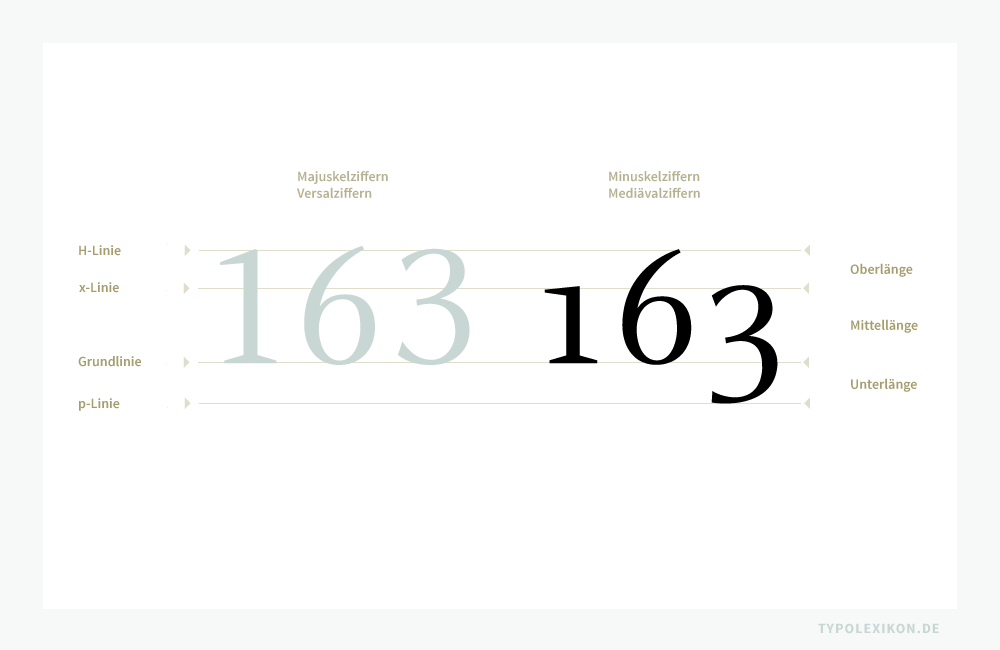
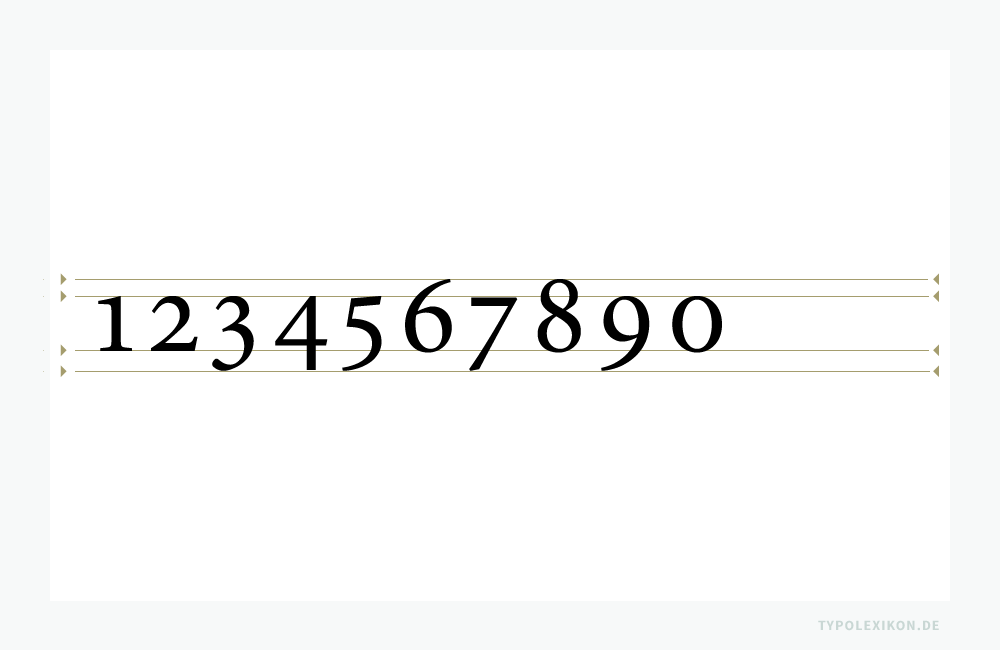
Etymologisch leitet sich »Minuskel« aus dem mlat. »minuscula (litera)« zu lat. »minusculus« für »etwas kleiner« zu lat. »minus« für »weniger, kleiner« und »Ziffer« aus dem arab. »as-sifr«, mlat. »cifra« oder »cephirum«, sphd. »zif(f)er« ab.
Minuskelziffern gibt es in der Schriftgattung Antiqua mit, ohne und mit betonten Serifen.
Das »Pendant« zu einer Minuskelziffer ist die Majuskelziffer.